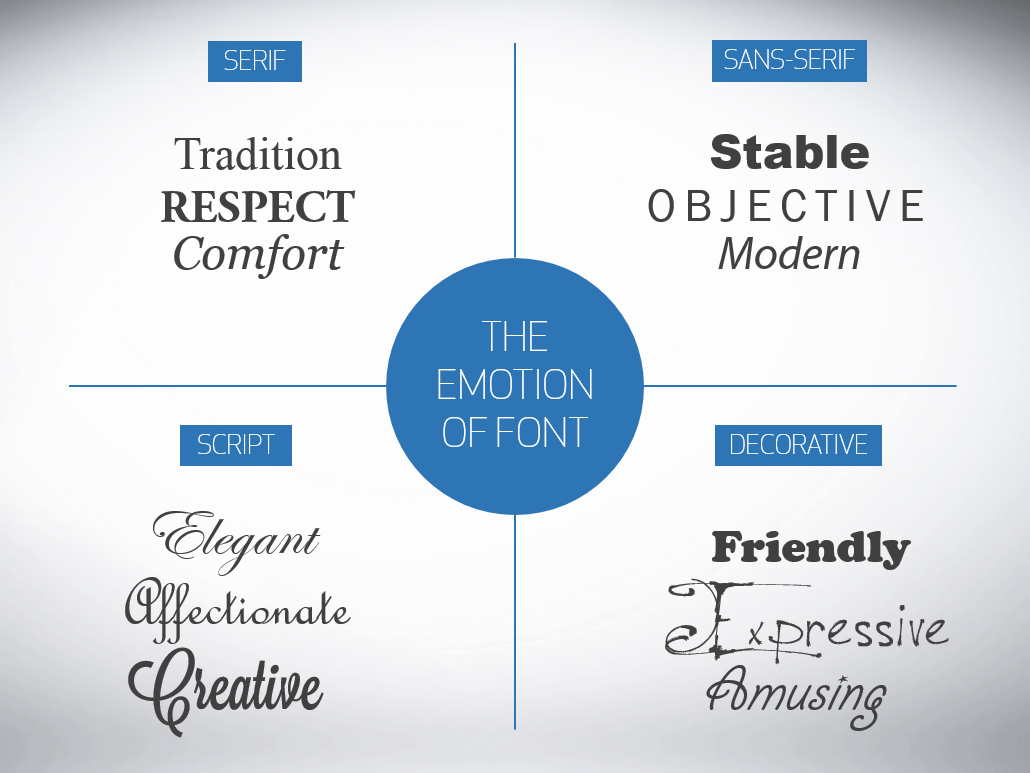
Scegliere un font è un lavoro da non sottovalutare. Ogni tipo di carattere racchiude dentro di sé uno stile proprio, un emozione che scaturisce nel vederlo. Partendo quindi dalle normali categorie in cui vengono oggi suddivisi i font: dalla macro suddivisione tra serif e sans serif fino alle sotto categorie, vediamo quali sono le relazioni tra emozioni e font.
Emozioni e font: qual è il legame
Ovviamente ogni scelta deve essere fatta tenendo conto dell’effettiva leggibilità del testo finale, fermo restando questa regola, quindi, vediamo com’è possibile individuare lo stile più adatto al nostro progetto.
Serif e sans serif
Partiamo quindi dagli stili detti con “grazie”, ovvero i serif. Questa categoria di caratteri trasmettono uno stile elegante e raffinato, attirano l’attenzione proprio perché le grazie che ricordano un po’ lo stile della scrittura a mano. Sono sicuramente più piacevoli da guardare, ma ricordate che tendono a stancare la vista sul lungo periodo, perché il testo risulta più difficile da decifrare per l’occhio. Per cui, in caso dobbiate usarlo per un testo molto lungo, fate attenzione. Tenente in considerazione che il lettore potrebbe abbandonare il contenuto prima del previsto, nonostante questo possa essere anche molto interessante.
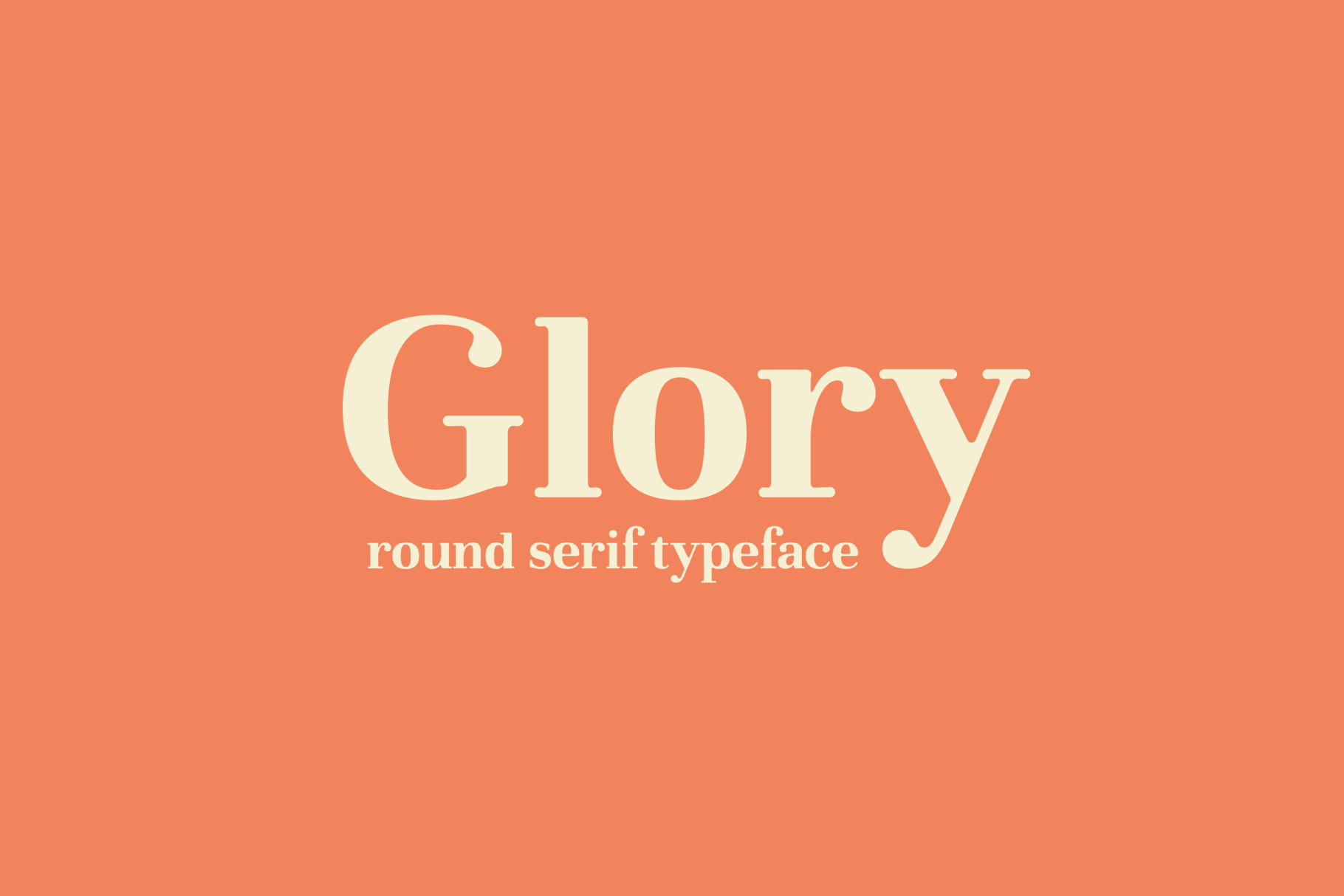
Solitamente, infatti, per testi lunghi si va ad utilizzare il sans serif, le lettere sono semplici e trasmettono ordine e chiarezza, ma sono anche molto minimali e alla lunga (se utilizzate per un intero progetto grafico) potrebbero dare un effetto banale. Per questo solitamente si tende ad utilizzare più font insieme. Un modo classico è quello di attirare l’attenzione con un titolo in serif e poi delegare al sans serif il testo completo affinché sia più semplice da leggere.
In mezzo troviamo i font semi-serif, che sono proprio una via di mezzo delle due categorie principali, il risultato è meno elegante e più semplice di un vero e proprio serif. Dalle grazie molto squadrate c’è anche la categoria del slab-serif, utilizzato molto per i testi dei libri, trasmette ordine e robustezza.
Gli altri tipi di font
Eccoci arrivati ai font che non fanno parte delle macro categorie serif/sans serif. Qui troviamo per esempio gli script: estremamente accattivanti ricordano la scrittura a mano, spesso sono anche molto articolati e presentano ghirigori, abbellimenti, sfumature ed effetti calligrafici. Sono associati prevalentemente ad aggettivi come: femminile, divertente e casual e sono adatti per progetti che parlano di creatività, romanticismo, emozioni o ricordi. Non possono essere utilizzati (un po’ come i caratteri serif) per un testo molto lungo, perché rischiano di confondere e stancare la vista. Sono invece perfetti per attirare l’attenzione per titoli o per sottolineare parti di testo in un progetto grafico.
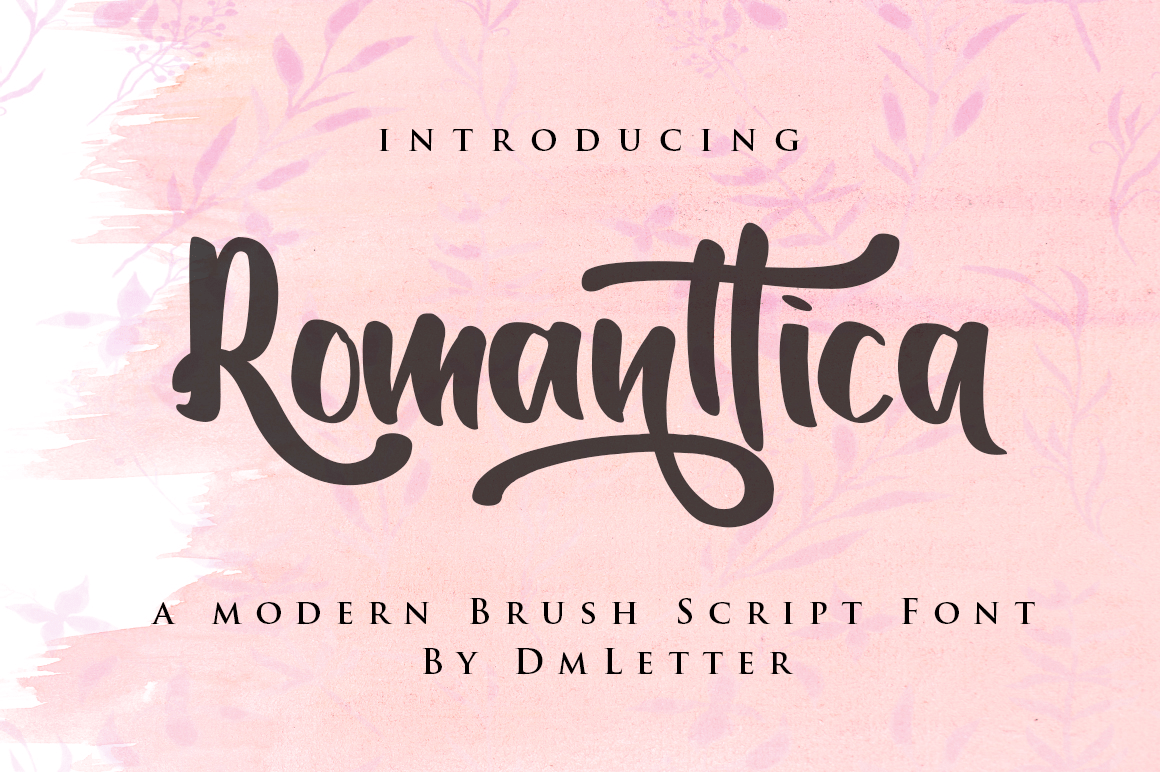
I font display sono più complessi perché includono davvero molti stili. Normalmente però, dato che ricordando i caratteri delle macchine da scrivere o per esempio del ciclostile, sono associati più ad aggettivi come: maschile, grossolano e assertivo. Questi font quindi sono più adatti a lavori che per esempio hanno a che fare con la tecnologia e che sono di base meno creativi. Anche in questo caso si sconsiglia di utilizzarli per lunghi testi ma solo per titoli e frasi da mettere in risalto.
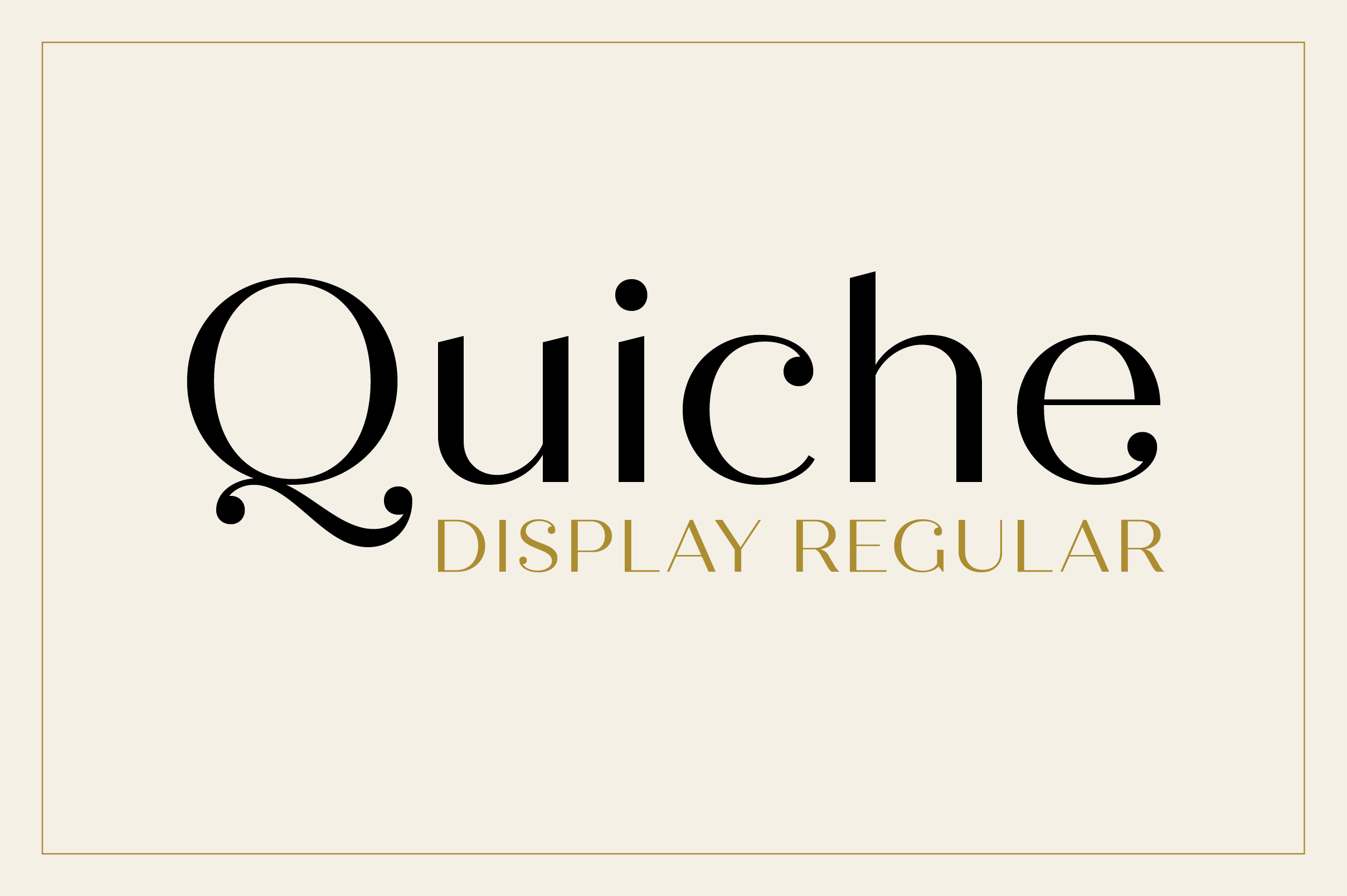
Per finire la rassegna di emozioni e font ecco i monospaced dall’aspetto più normale e senza fronzoli sono assimilabili ai sans-serif per cui sono adatti alla scrittura di lunghi testi, senza stancare la vista.